InstagramなどのSNSでは、写真にあえて手書き風の文字を入れるのが流行中です。
打ち込み文字にはない個性や温かみを演出できる手書きフォント、実はアプリを使えば簡単に書けちゃいます。
そこで、今回の記事では手書き文字アプリ5選の紹介とスマホで写真におしゃれな手書きフォントを入れる方法をご紹介します。
手書き文字アプリ5選の紹介
流行りの手書き風フォントがたくさん『YouCamアプリ』
『YouCamアプリ』は、走り書き風フォントや流行りのプリクラ落書きフォントなど、日本語だけでも50種類以上のおしゃれな手書き風フォントが搭載されている手書き文字アプリです。
インスタ映えする手書き風フォントで写真にさくっと文字入れできるので、初心者でもデザイナー並みの画像を気軽に作成できます。
一緒に使うと相性抜群の雑誌風コラージュ機能や吹き出し機能が充実しているのも嬉しいポイントです。
✅AIでおしゃれな手書き文字加工
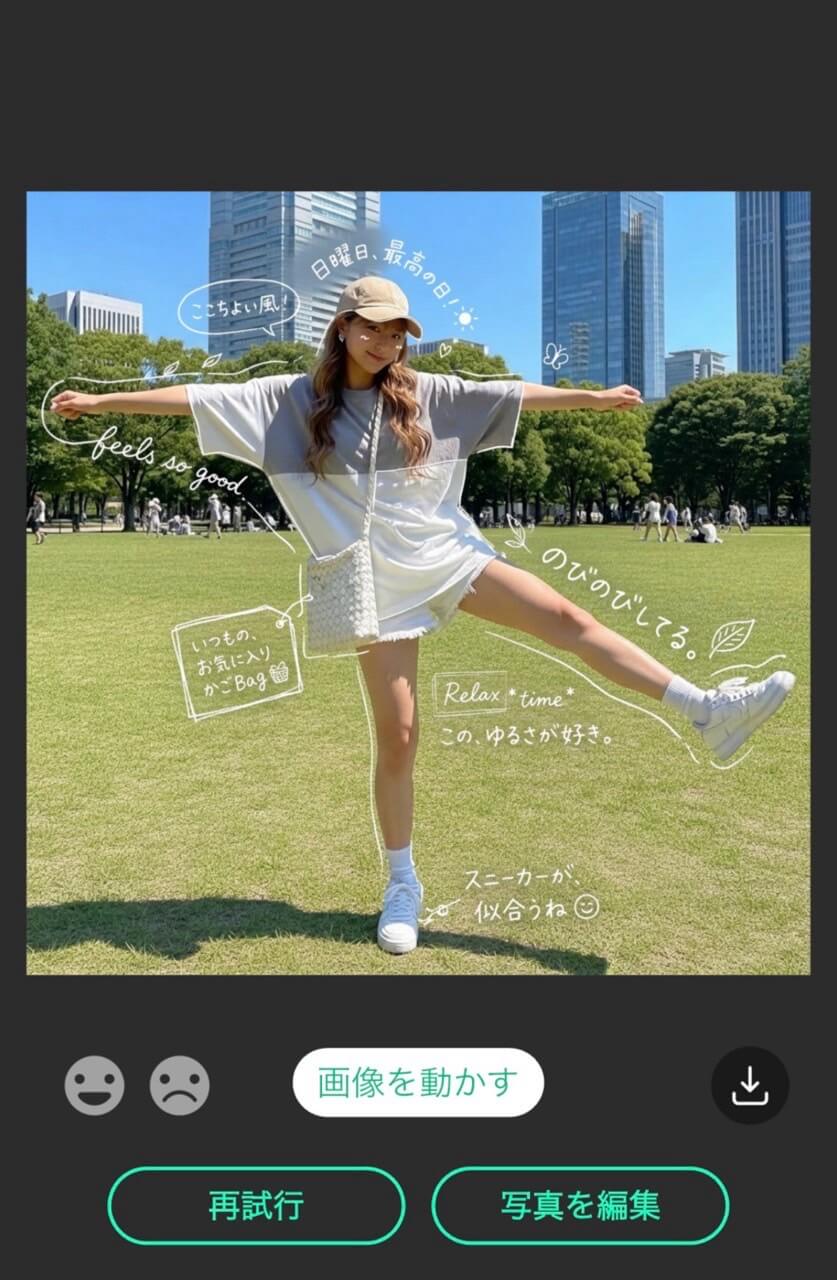
「YouCamアプリ」アプリの【i2i画像生成】を使うと流行りの白文字手書き加工に!
カフェの写真やペットの写真にもかわいく手書きの文字が生成されます。
- プロンプトにこちらをコピペ:元の写真は変えず、それぞれの被写体に対して写真や被写体と深く関連のある手描き風テキストを自然に配置。線は白ペンで描いたような細めのタッチで、一筆書きのようにラフで横に流れる個性のあるリアルな手書き文字。インクのような滲みを生かした強弱あり手書きフォント。オブジェクトの輪郭には細い線でデコレーションを加え、吹き出しや囲みも適宜追加。テキストは日本語の手書き文字で、ひらがなを6割ほど使い、残りは漢字や英語を自然に混ぜる。トーンは雑誌風、温かみのある感情に寄り添ったような言葉を選ぶ。装飾は元の写真のイメージにあった小物やオブジェクトをごく控えめに加え、余白を大切にしたラフメモ風・ins風の、おしゃれで力の抜けたナチュラルライフデザイン
手書き文字を自分好みに調整できる『Canva』
『Canva』には、日本語、英語、中国語、韓国語など様々な言語の手書き文字フォントが搭載されています。
豊富なテンプレートやステッカーと合わせて使って、サムネイル画像やポスターを作成するのにも便利です。
日本語の縦書きに対応しているのも嬉しいポイントです。
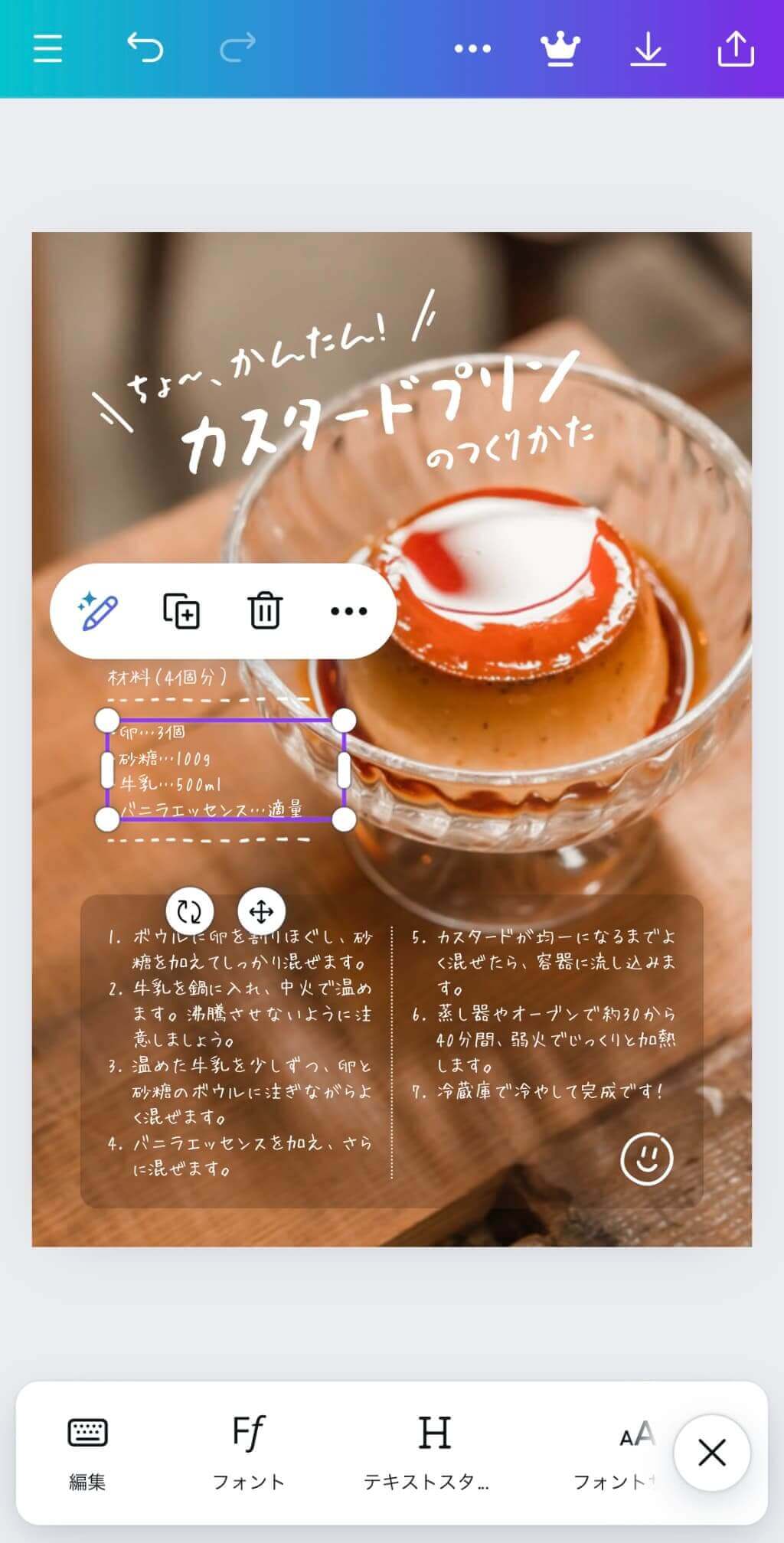
手書きブラシで可愛い文字が書ける『BeautyPlus』
『BeautyPlus』では質感が可愛い手書きブラシで、写真に直筆の文字を入れることができます。
文字以外にもハートなどをちょこっと描いてみても可愛いです。
オリジナリティのある手書き文字を書きたい人は、ぜひ使ってみてください。
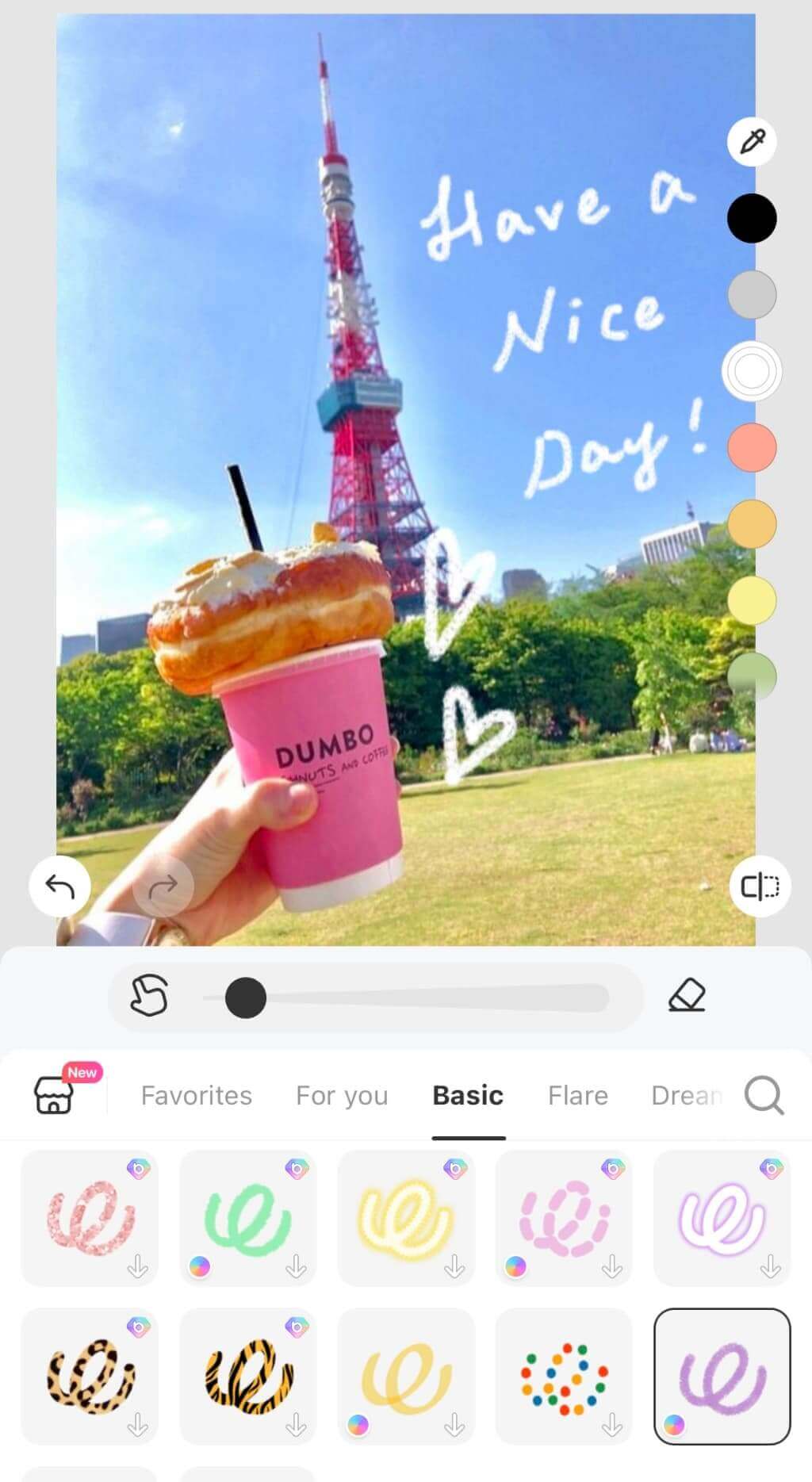
選べる手書き風フォントが豊富『Phonto』
『Phonto』は、写真の文字入れに特化したアプリです。
400種類以上のフォントが用意されており、日本語の手書き文字も充実しています。
手書き文字の字間変更や枠線の追加、影の調節など、スマホでも高度な文字入れが可能です。
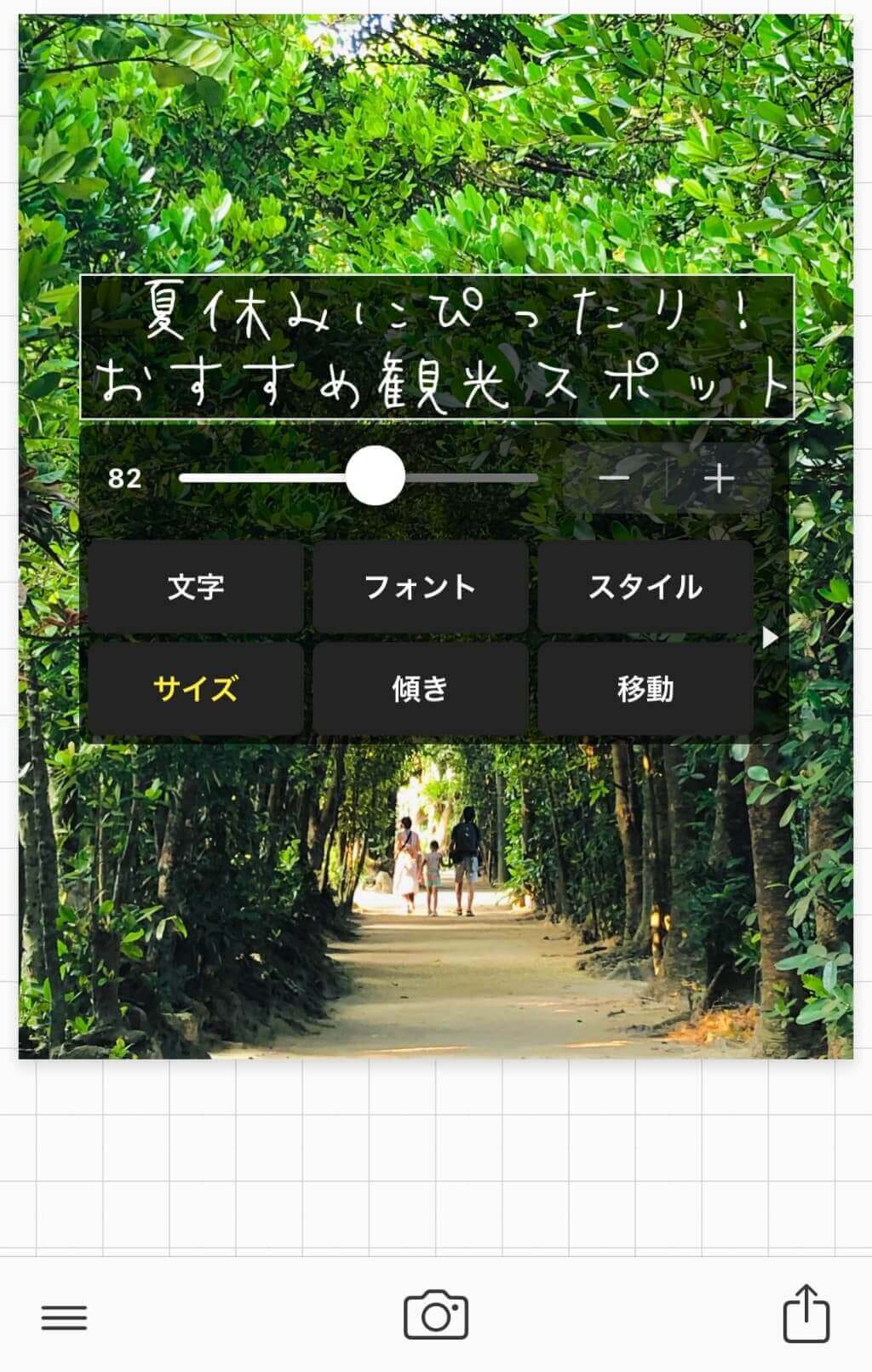
気軽に手書き文字が使えるアプリ『LINE Camera』
「簡単な操作でさくっと手書き文字で写真を加工したい」という方には『LINE Camera』がおすすめです。
数ある手書き文字アプリの中でも使いやすさが抜群なので、文字入れ加工デビューにも最適です。
可愛い手書き文字を写真やイラストに追加できるほか、一緒に使うとおしゃれに仕上がる吹き出しなども用意されています。
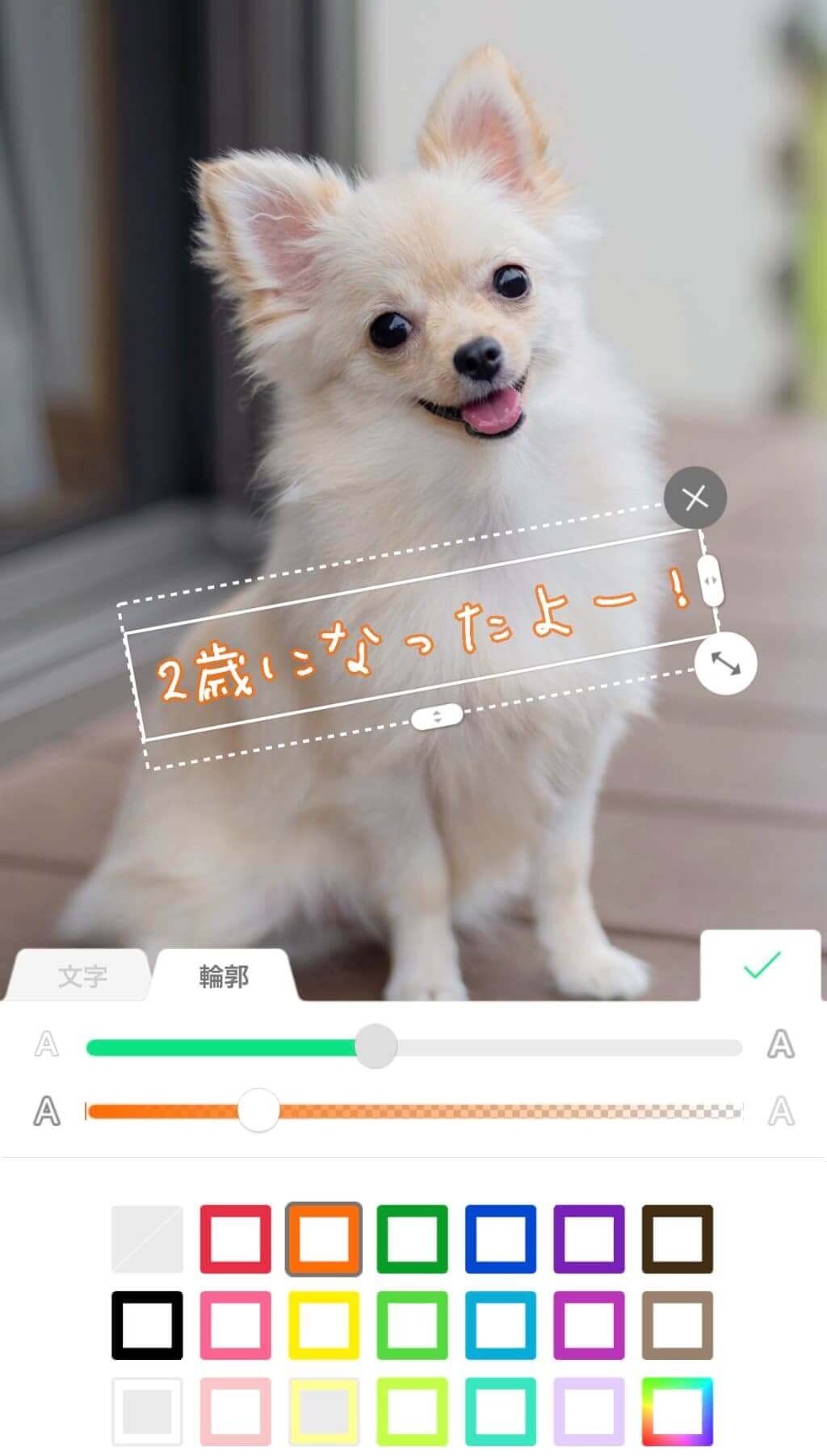
手書き文字アプリでかわいいフォントを入れる方法
ここからは、今回ご紹介したアプリ『YouCamアプリ』を使って画像におしゃれな手書き風フォントを入れる方法をステップ別に説明します。
入力用手書き文字加工指示(プロンプト):
元の写真は変えず、それぞれの被写体に対して写真や被写体と深く関連のある手描き風テキストを自然に配置。線は白ペンで描いたような細めのタッチで、一筆書きのようにラフで横に流れる個性のあるリアルな手書き文字。インクのような滲みを生かした強弱あり手書きフォント。オブジェクトの輪郭には細い線でデコレーションを加え、吹き出しや囲みも適宜追加。テキストは日本語の手書き文字で、ひらがなを6割ほど使い、残りは漢字や英語を自然に混ぜる。トーンは雑誌風、温かみのある感情に寄り添ったような言葉を選ぶ。装飾は元の写真のイメージにあった小物やオブジェクトをごく控えめに加え、余白を大切にしたラフメモ風・ins風の、おしゃれで力の抜けたナチュラルライフデザイン
アプリで手書き文字を入れた画像が完成!
約30秒ほど待つだけで、あっという間にとってもかわいいセンス良さげな手書き文字加工ができちゃいました!⭐🎨
手書き文字アプリの使い方の例
ここでは、手書き文字アプリの便利な使い道をいくつかご紹介します。
以下は、上でご紹介したアプリでできる手書き風加工の例です。
①SNSのサムネ画像を手書き文字で盛る
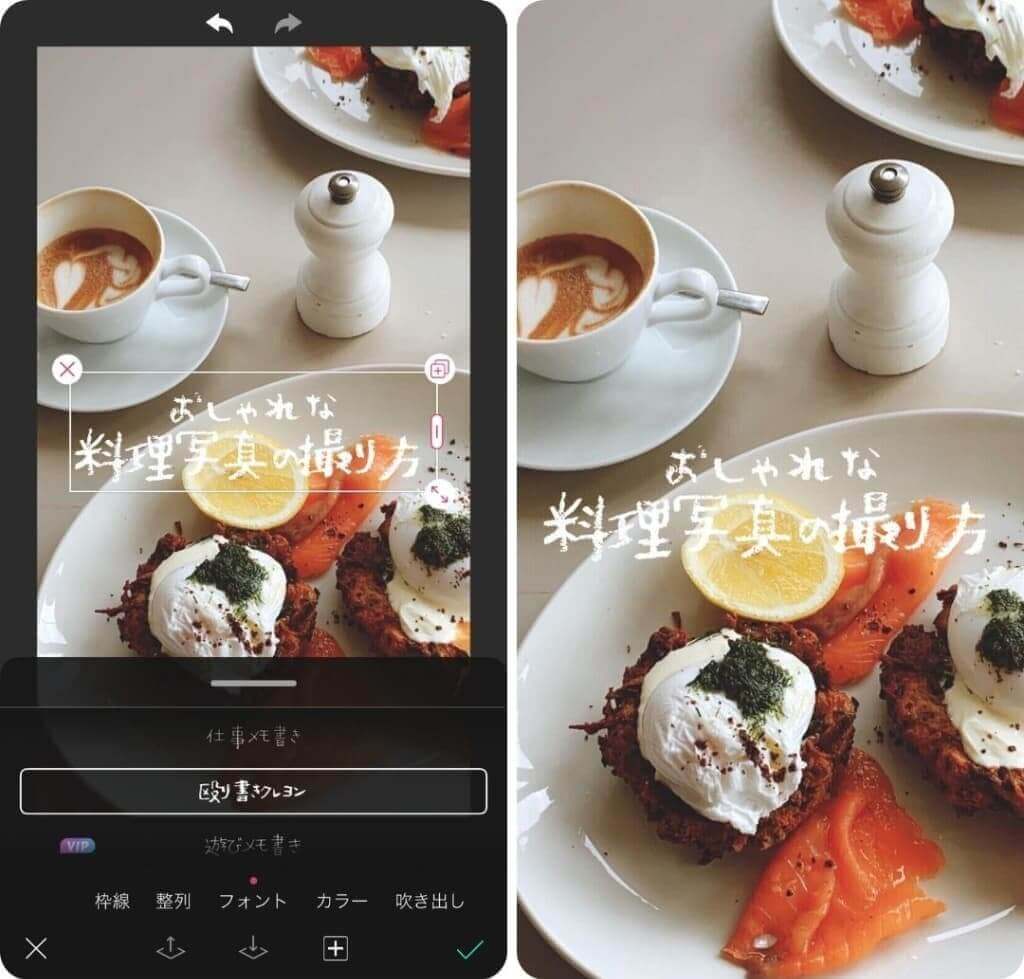
インスタやTikTokの投稿では一枚目のサムネイル画像でユーザーの目を引くことがとても大切です。
料理やインテリアグッズ、コーデなどのサムネ画像に手書き文字を入れれば、雑誌の表紙のようなおしゃれな投稿で印象に残りやすくなりますよ。
②手書き風メッセージカードを作成
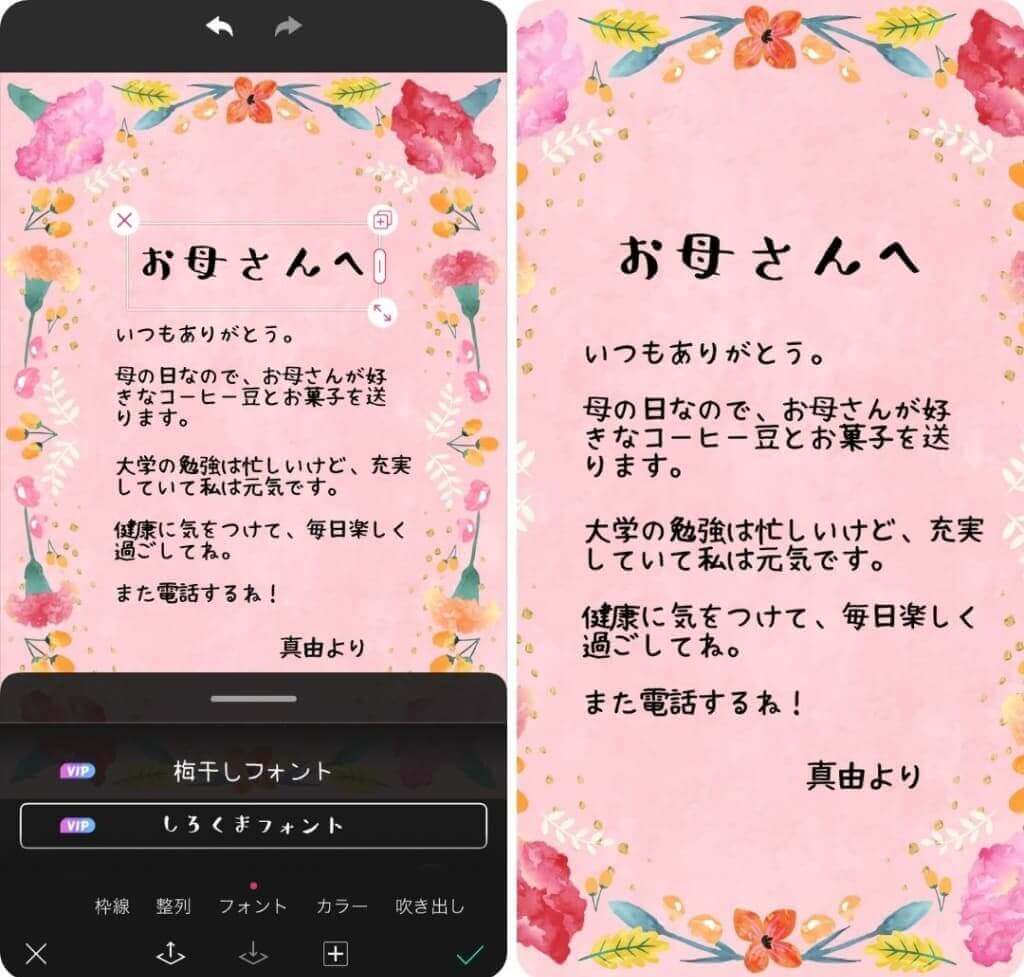
最近では誕生日やクリスマスなどのお祝い事にデジタルメッセージカードを書く方も増えてきています。
手書き文字アプリは、そのようなデジタルメッセージカードに親近感を出したい際にもおすすめです。
③可愛い平成風のプリクラ落書き
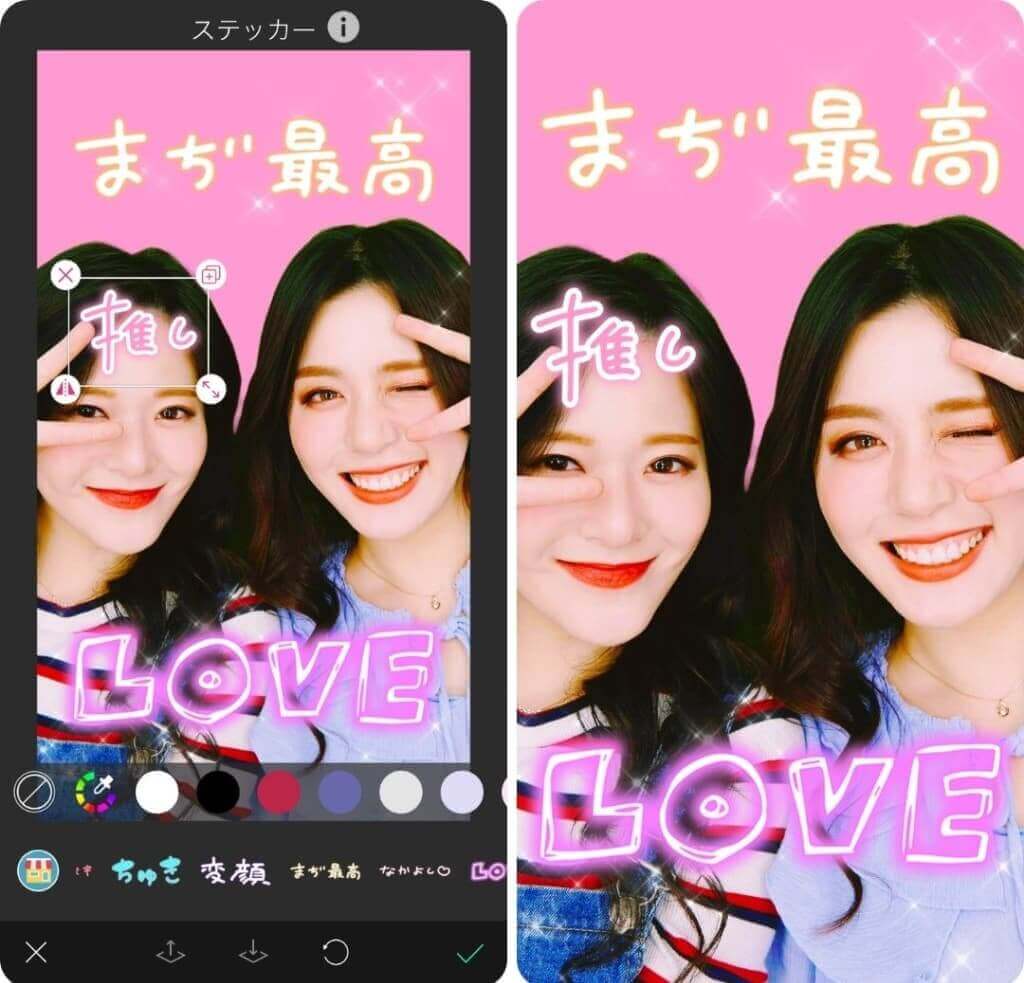
プリクラで写真を撮る際に時間が足りず、何も書いていないまま「落書きタイム終了!」となってしまった経験ありませんか。
プリクラ風手書き文字ステッカーやらくがきペンが搭載されたアプリなら、後から自分好みにプリクラに文字入れできますよ!
まとめ
以上、今回の記事ではスマホでおしゃれなフォントを入れられる手書き文字アプリ5選をご紹介しました。
本記事でご紹介したように、最近ではスマホアプリでもおしゃれな手書き文字入りの画像を簡単に作成できるようになりました。
インスタのストーリー投稿やデジタルメッセージカードに手書き文字を加えれば、それだけで一気に垢抜け感が演出できます。